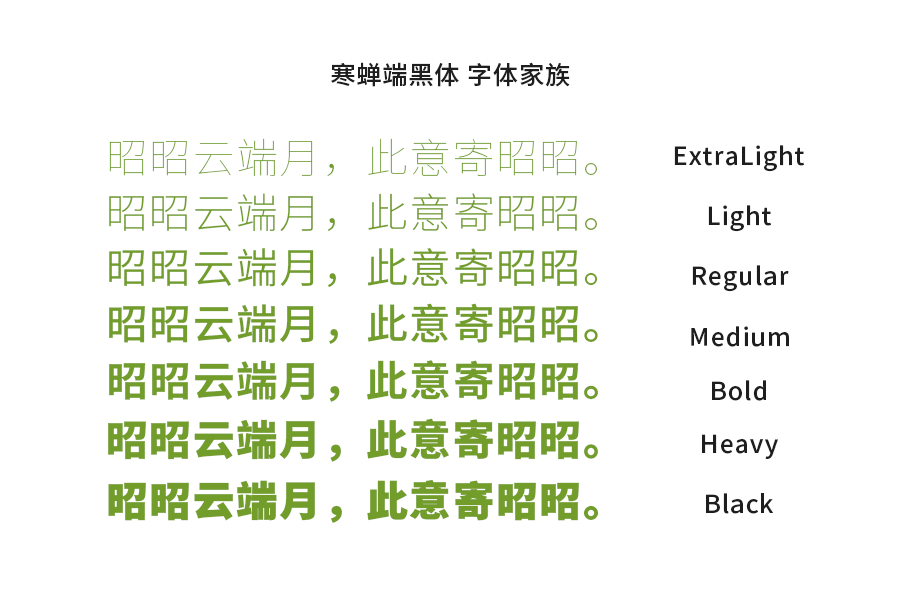
在数字时代,文字不仅是信息的载体,更是审美与体验的双重展现。今天,为您推荐两款免费且极具设计感的黑体字体家族,它们都以简洁、易读为核心,为您的阅读与设计带来全新的视觉享受。
vivo Sans,作为vivo品牌专属定制字体,设计理念回归文字本质,摒弃繁复装饰,专注于精细结构优化。9款不同字重,从轻盈到厚重,满足不同阅读与设计需求。vivo Sans以其清晰易读的文字效果,让用户在阅读时更加专注于内容本身,享受纯净的阅读体验。无论是移动应用、网页浏览还是文档编辑,vivo Sans都能为您带来流畅、舒适的视觉享受。
2.寒蝉端黑体
寒蝉端黑体,基于开源字体思源黑体重新插值生成,保留了其精髓,共计7款字重。寒蝉端黑体以其简洁、大方的设计风格,无论是紧凑排版的窄体,还是开阔视野的宽体,都能轻松应对。其细腻的笔画处理和均匀的字体间距,确保了文字在不同场景下的可读性和美观性。寒蝉端黑体不仅适合各类数字屏幕的展示,也是设计师和开发者在创作中的理想选择。
两款字体家族,各具特色,共同诠释了简洁与易读的设计之美。无论是追求极致阅读体验的vivo Sans,还是兼具宽窄之美的寒蝉端黑体,都将是您数字生活中不可或缺的伙伴。立即下载体验,让文字成为您生活中的一道亮丽风景线。